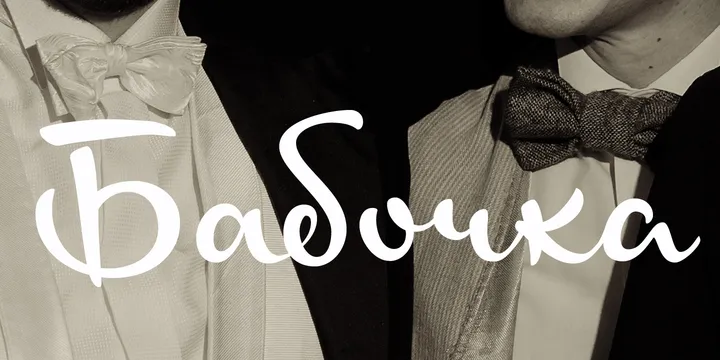
Шрифт Josef K
Это профессиональный каллиграфический шрифт Josef K Paneuropean, разработанный дизайнером Юлией Сюсмяляйнен. Продукт представляет собой готовый цифровой актив для использования в графическом дизайне, верстке, оформлении полиграфической продукции или веб-интерфейсов. Шрифт отличается уникальной эстетикой ручного письма, что придает текстовым блокам индивидуальный и выразительный характер.
- Поддержка кириллического алфавита: шрифт полностью адаптирован для работы с русским языком, что позволяет использовать его в полноценных текстовых композициях.
- Каллиграфическая стилистика: визуальное исполнение имитирует живое письмо, сохраняя при этом высокую читаемость и техническое качество начертания.
- Универсальность применения: подходит для создания заголовков, логотипов, оформления приглашений, открыток и других дизайнерских проектов, требующих акцентной типографики.